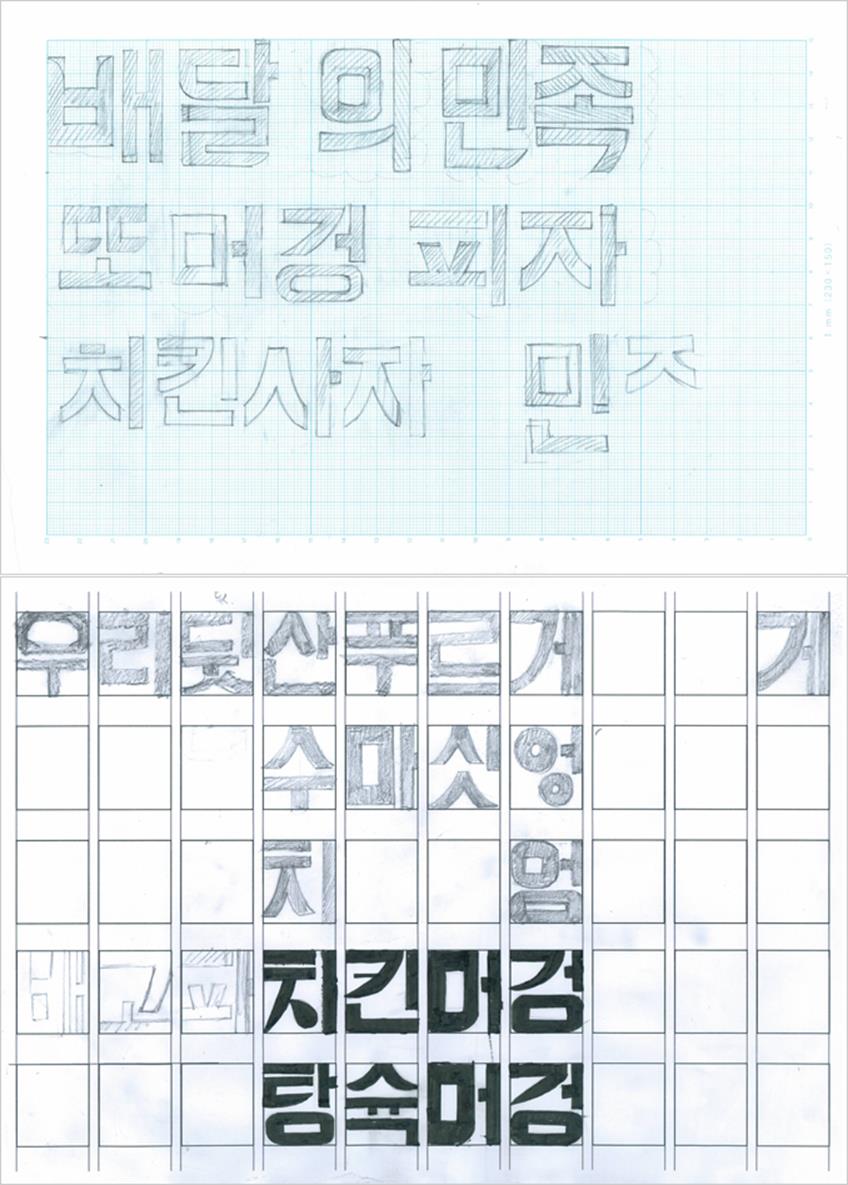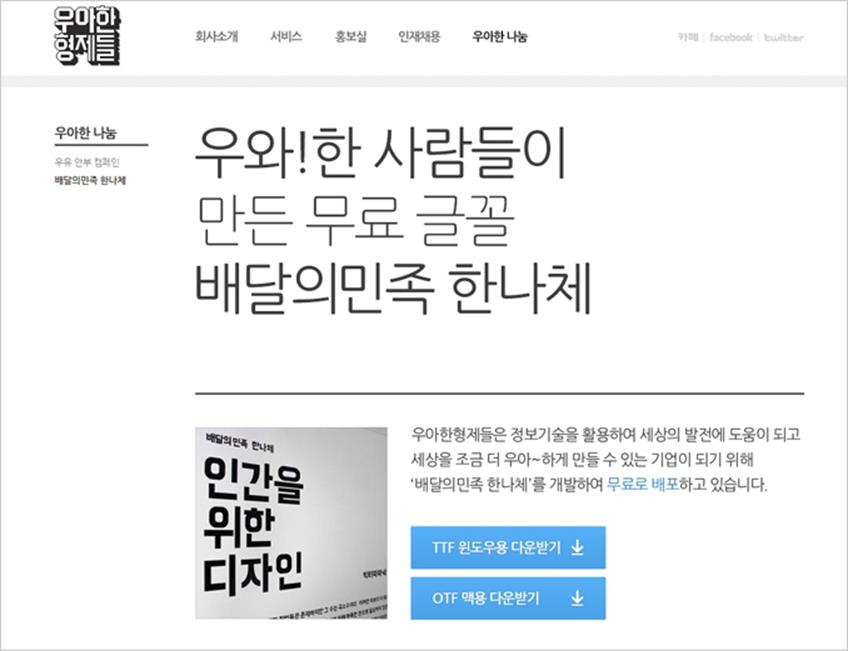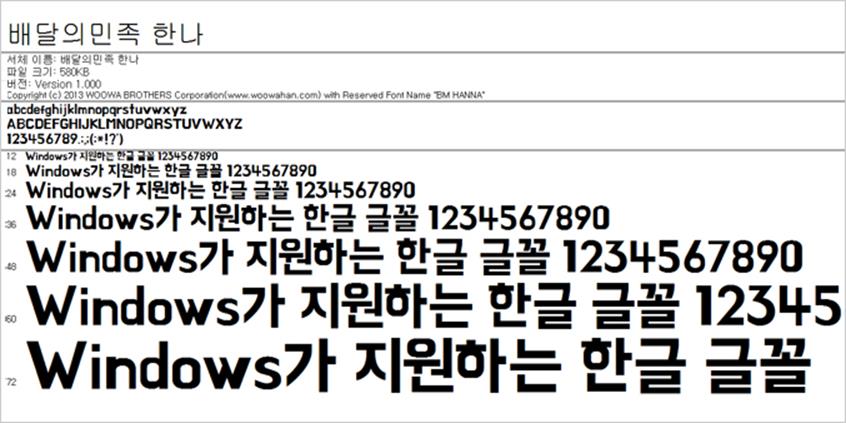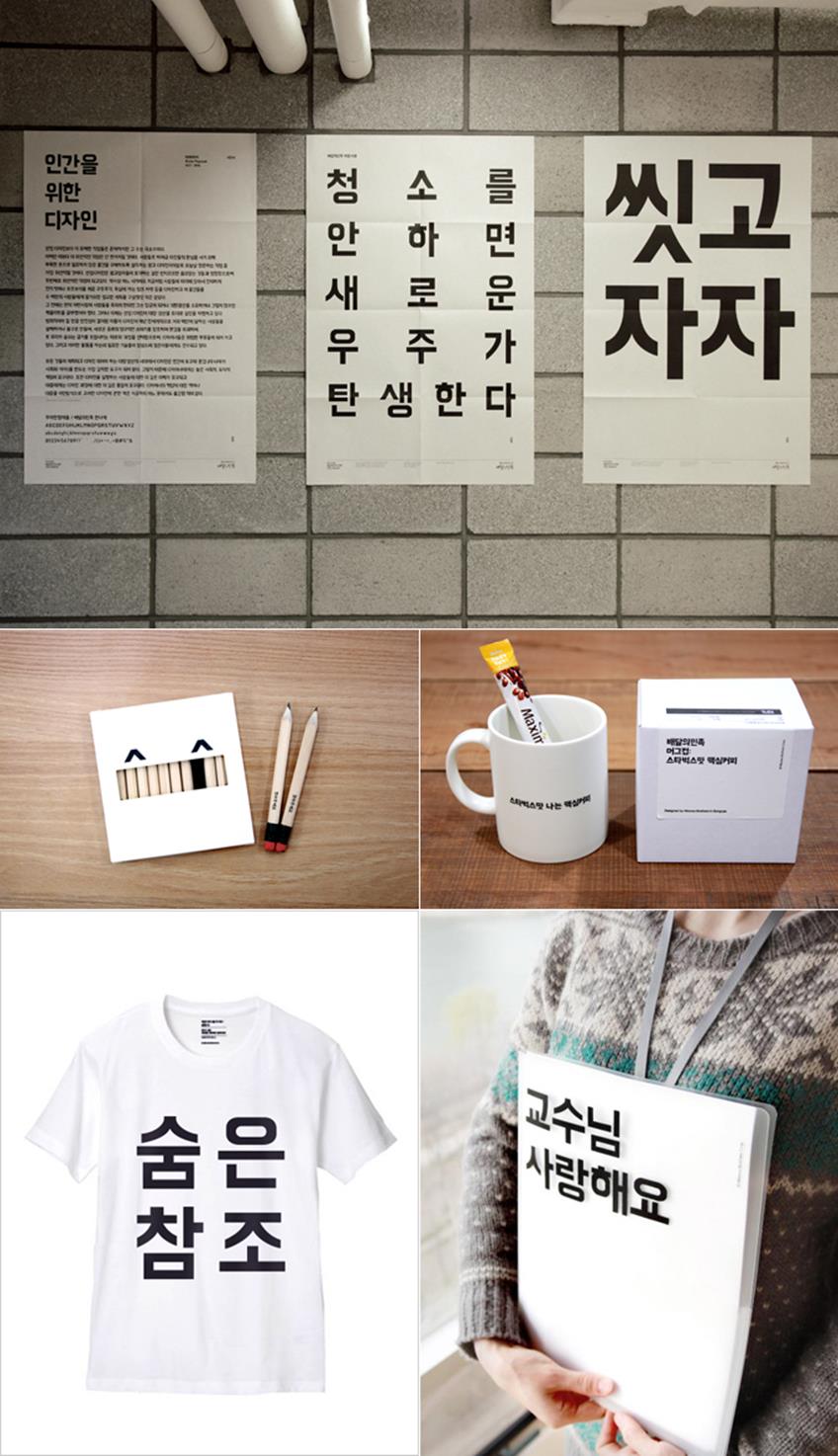
우아하게 경영하는 디자이너, 김봉진
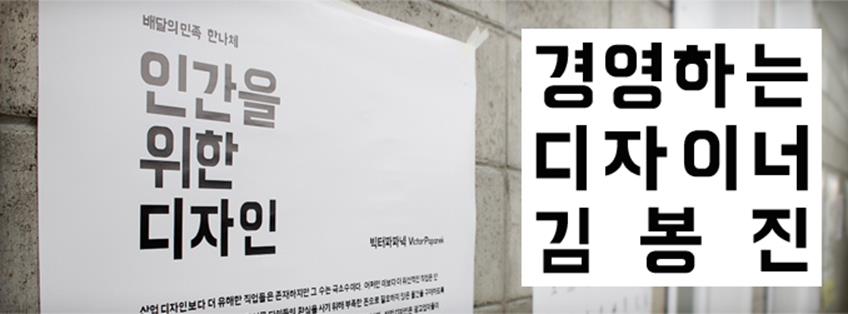
대표님 안녕하세요. 모르는 분이 많지 않겠지만, 간단한 소개를 부탁 드릴게요.
안녕하세요. 저는 우아한형제들(www.woowahan.com)의 김봉진 대표입니다. 우아한형제들은 ‘배달의 민족(www.smartbaedal.com)’이라는 애플리케이션을 개발한 곳이에요. 현재 위치를 중심으로 가장 가까운 배달 업소를 알려주는 서비스죠. 메뉴이미지, 업소 상세정보, 이용후기 등을 제공해 편리하게 배달 음식을 주문할 수 있도록 도와주는 앱이에요. 얼마 전 600만 다운로드를 돌파했고, 5월에는 구글(Google) 초청으로 세계개발자대회(I/O)에도 참석합니다. (웃음) 그리고 저는 2000년도부터 시작해 만 14년 정도 웹 디자이너로 일해온 디자이너이기도 합니다. 네오위즈, 이모션 등에서 경험을 쌓고 한때 인테리어 분야 창업을 했다가 한차례 실패해 보고, NHN과 플러스엑스를 거쳐 지금의 우아한형제들을 창업해 배달의민족 서비스를 만들어 사업을 키워나가고 있죠.
김봉진 우아한형제들 대표
웹 디자이너로 활약하실 때 처음 뵙고, 인테리어 사업을 시작하실 때 마지막으로 인사 드렸는데, 그 이후에 많은 변화가 있었네요.
10년 차 디자이너가 되면 ‘나는 어떤 디자이너로 성장해야 하나?’ 진지하게 고민을 하게 됩니다. 그때 인테리어 관련 사업(봄봄하우스)을 하겠다는 계획을 하고 준비하기 시작했죠. 결국 그 일은 실패했어요. 판매하던 가구와 소품들은 예쁘고 완성도가 높았지만 문제는 제품이 비싸서 팔리지 않았다는 거죠. 그땐 몰랐어요. 많은 디자이너들이 나중에 돈을 모으면 멋진 카페나 펜션을 꾸며 운영하겠다는 계획을 세우지만, 간판이나 메뉴판만 그럴듯하게 만든다고 해서 성공하지 못하는 것과 같죠. 원두 고르는 법이나 에스프레소 추출법도 모르는데 카페가 잘 될 리 없잖아요.
저도 가구의 원가, 물류비 등을 전혀 공부하지 않고 시작했기 때문에 팔수록 손해 보는 상황이었어요. 실패하고 많이 낙담하긴 했지만 의미 있는 경험이었습니다. 그리고 나서 NHN에 2년 정도 있었어요. 그때 많이 배우고 자극도 받았죠. NHN의 젊은 디자이너들과 UXDP 행사에 참여한 머리 좋고 감각적인 대학생들을 보면서 다시 디자인을 배워야겠다는 생각이 들었죠. 포토샵만 잘 해서는 더 이상 성장하긴 어렵겠구나 싶었어요. 본질에 대한 공부와 고민이 필요한 시점이었죠. 디자인 기능공처럼 클라이언트 요구에 맞춰 기계처럼 시안을 만들어내고 PSD 파일을 예쁘게 꾸미는 작업만 해서는 안되겠다 싶었습니다. 그때부터 텍스트가 있는 책을 보고 대학원에 들어가 공부를 시작했죠.
김봉진 대표가 진행했던 프로젝트.
위에서부터 현대카드(2004년), 나이키(2003년), 네이버(2009년)
새로운 도약의 발판이 되어준 ‘배달의민족’은 어떻게 만들어졌는지 궁금합니다.
저는 신명섭, 변사범 디자이너와 함께 플러스엑스(www.plus-ex.com)를 시작했던 창업멤버에요. ‘배달의민족’ 서비스는 플러스엑스의 토이프로젝트였죠. 전략적으로 비즈니스 해야겠다는 생각 없이 주변 사람들이 쓰면 좋겠다는 생각으로 만들었는데 기대 이상의 인기를 끌게 되었어요. 첫 사업을 실패할 때도 느꼈지만 ‘세상은 내가 계획한대로 돌아가지 않는구나’ 싶었죠. 예상하지 못했던 곳에서 제 갈 길을 찾게 된 것 같아 신기했어요.
우아한형제들을 기점으로 ‘디자이너’에서 ‘경영인’으로 모드가 전환된 건 아닌가요?
제 중심은 항상 디자이너에요. 저는 스스로 ‘경영하는 디자이너’라고 정의합니다. ‘디자이너 출신’이란 표현은 과거형이잖아요. 계속 디자인을 하고 있기 때문에 ‘경영’을 앞에 붙였어요. 수많은 CEO들이 경영학적으로 디자인을 논하며 ‘디자인경영’을 말하지만 미술 전공자가 경영을 이야기해도 재미있을 것 같아요. 이미 실리콘벨리에서는 경영하는 디자이너를 어렵지 않게 볼 수 있어요. 회사 가치가 2조를 넘는 에어비엔비(www.airbnb.co.kr) 대표도 디자이너이고 그루폰(www.groupon.com)을 만든 사람도 웹디자이너 출신이에요. 유투브의 공동창업자도 디자이너죠. 그쪽에선 디자이너스펀드가 만들어져 활성화되어 있을 정도에요.
이젠 감성이 중요한 시대입니다. 개발자와는 다른 관점에서 디자이너의 강점이 발현되는 부분이 많다고 생각해요. 새로운 가능성을 보여줄 수 있다고 믿습니다. 브랜드를 만들어가는 일관성, 인사정책, 커뮤니케이션 방법, 의사 결정 방법도 달라요. 예를 들어, 우아한형제들에서는 직원들의 의견을 모아 버킷리스트(bucket list)를 만들어요. 직원들이 원하는 회사 모습을 함께 그리고 공유하는 시스템이죠. 단순히 “우리 이렇게 해요”라는 구호를 적고 파워포인트로 보여주거나 사장님 훈시처럼 액자에 담아 걸어두는 방식이 아니라 포스터를 만들어 사무실 곳곳에 부착해 직원들과 커뮤니케이션 하고 비전을 명확하게 전달하는 방식이죠.
저는 계속 디자인을 하고 있어요. 디자이너가 아니면 생각하기 어려운 다양한 시도를 하고 있습니다. ‘한나체’라는 폰트를 만든 것도 그렇고 어렵게 만든 폰트를 무료로 배포하겠다는 생각도 회사 대표가 디자이너가 아니었다면 쉽게 이루어지지 않았을 거에요. 대기업이 아닌 이렇게 작은 조직에서 그런 일을 계획하고 결정하기는 쉽지 않죠.
배달의민족의 전반적인 디자인 컨셉이나 전략에 대해 소개해주세요.
저는 일을 시작하기 전에 먼저 정의를 내려봐요. 책을 보면서 전략과 컨셉을 만들어가는 방식을 공부하고 제게 맞는 방식을 찾은 거죠. 예전엔 그러지 않았어요. (웃음) 예를 들어 ‘커피’에 대한 사전적 의미를 찾고 나만의 커피를 정의 내리는 거죠. 배달 음식점을 알려주는 서비스를 만들어보자고 했을 때에도 ‘배달 음식’에 대한 정의를 내리고 디자인과 브랜드를 고민하기 시작했어요.
저는 ‘배달 음식’ 하면 국가대표 축구 경기를 할 때 친구들과 치킨에 맥주를 배달해 먹었던 시간, 밤 11시가 넘는 시간까지 직원들과 일하다 족발에 보쌈을 배달해 먹으며 토론을 이어가던 시간들이 생각났어요. 그래서 “아, 배달 음식이란 사랑하는 사람들과 나누는 행복한 시간이구나!”했던 거죠. 그렇기 때문에 배달 음식을 검색하고 찾는 과정도 즐겁고 재미있으면 좋겠다고 생각했어요. 애플리케이션을 구동하는 순간부터 재미있게 만들자. 그래서 이름도 ‘배달의민족’이라고 정하고 ’21세기최첨단 찌라시’, ‘전단지백과사전’과 같은 카피들도 직접 생각해냈죠.
우아한형제들 CI, 배달의 민족 BI, 이벤트 페이지, 캐릭터 모음
전반적인 디자인은 홍대 문화를 좋아할법한 대학생을 대상으로 삼고 키치, 패러디 등과 같은 키워드에 접목했어요. 이미 <무한도전>, <컬투쇼>와 같은 비주류 느낌의 문화 코드가 자리를 잡고 인기를 끌고 있잖아요. ‘쌈지’의 디자인 느낌을 좋아해서 참고하고 메인 폰트는 윤디자인의 사춘기체로 정했죠. 사춘기체를 메인 폰트로 사용한 건 무리라는 의견이 많았지만 과감하게 사용했어요. 그렇게 아이덴티티가 다져졌죠. 배달의민족이 인기를 끌면서 우후죽순 사춘기체를 너무 많이 사용해 우리만의 폰트를 만들어보자는 생각을 갖게 되기도 했죠.
일반적인 브랜드들이 정중한 학생회장 느낌에 머리도 좋고 운동도 잘하는 ‘엄친아’ 스타일을 추구했다면, 우리는 박명수처럼 친근한 동네 형 느낌을 추구했습니다. 애플이나 네이버, 현대카드 등의 브랜드가 차지하고 있는 영역은 모두 비슷해요. 스마트하고 세련되고 고급스럽죠. 반면에 우리는 그 반대편에 있는 B급, 키치, 저속, 패러디 등의 키워드가 어울리는 영역을 선택했죠. 브랜드는 세련되어야 한다고 생각하지만 우리는 타깃도 다르고 관점이 다르기 때문에 의도된 저급 컨셉으로 전략을 짜고 움직인 셈이죠.
최근 송파로 사무실을 이전하시면서 인테리어에도 굉장히 신경을 많이 쓰신 것 같은데요. 공간에 대한 소개도 부탁 드릴게요.
제가 직접 설계하고 디자이너와 세부적인 아이디어를 나눠 공간을 꾸몄어요. 우아한형제들의 사람들이 머무는 공간은 어떠해야 하는지 우리 스스로 하나씩 풀어갔죠. 특징 중 하나는 대회의실 문을 모두 개방할 수 있는 폴딩 도어로 만들었다는 점이에요. 문을 모두 열면 80여 명이 강의를 들을 수 있는 공간이 확보되죠. 대회의실은 가장 낭비가 심한 공간이에요. 회의가 이루어지지 않을 땐 거의 죽어있는 공간이죠. 그래서 사용하지 않을 땐 카페처럼 열어둘 수 있게 했습니다. 우리처럼 작은 회사에서는 공간을 최대한 효율적으로 쓰는 방법을 고민하게 됩니다. (웃음) 위치 선정은 앞서 얘기한 버킷리스트에 의해 정해졌어요. 번잡한 강남 한복판 말고 공원이 옆에 있는 한적한 곳에서 일하고 싶다는 직원들이 많았어요. 공간을 찾던 중에 마침 석촌호수를 앞에 두고 매직아일랜드와 송파나루공원이 있는 이곳을 운 좋게 찾게 되었죠. 전철역에서 15분 정도 걸어와야 하는 위치에 있지만 공원을 끼고 걸어오는 길이 좋아요. 공간 내부는 피터팬에 나오는 네버랜드가 컨셉이에요.
우아한형제들 사옥에 대한 계획도 있나요?
사옥을 직접 설계하고 짓는 일은 많은 디자이너들이 꿈꾸는 일 아닐까요? (웃음) 몇 년 후에 실현 가능할지 모르겠지만 꼭 해보고 싶은 작업이에요. 우아한형제들 사옥 1층과 2층에는 어린이 집을 만들고 싶어요. 사원 복지를 위한 일이기도 하지만 디자이너가 만드는 어린이 집은 어떤 모습이 될지 궁금해요. 생각만해도 설렙니다. 어린이를 위한 교육 공간, 아기와 엄마 그리고 선생님 사이의 정서적 교감, 많은 사람들의 경험을 모두 고려해 디자인해야 특별한 공간인만큼 굉장히 재미있을 것 같아요. 물론, 사옥에 대한 이야기는 어디까지나 꿈입니다. (웃음)
회사 운영이나 직원과의 관계에서 가장 중시하고 신경을 쓰는 부분은 무엇인가요?
‘성장’입니다. 10년 넘게 직장 생활을 해봤고 이제 14년 차에 접어드는데요. 가장 아름답고 행복하게 기억하는 순간은 많은 월급과 좋은 복지 때문이 아니었어요. 죽도록 일했지만 이모션(www.emotion.co.kr)에서의 시간들이 소중한 이유는 함께 꿈을 나누며 성장했던 친구들이 있었기 때문이에요. 이모션은 제게 친정 같은 회사죠. 그때 지금 이루고 있는 네트워크 기반을 형성했고, 그 시절 열심히 일한 덕분에 많은 분들이 ‘김봉진’ 하면 성실한 친구로 기억해주고 있어요. 힘들었지만 돌이켜보면 그때가 가장 행복했고, 제가 가장 많이 성장했던 시절입니다.
우아한형제들의 명함이, 우리 공간이, 우리 디자인이 누군가에게 이야기 거리가 되면 좋겠어요. 단순히 “예쁘다”로 끝나지 않고 다른 사람을 만났을 때 우아한형제들의 명함과 공간이 어떻더라고 재미있게 전하고 싶은 재미와 즐거움을 줄 수 있으면 좋겠어요. 그런 재미있는 장치들이 모여 자연스럽게 우아한형제들의 문화가 된다고 생각합니다. 브랜드 위에 문화가 있어요. 백제와 고구려가 망해도 그들의 문화가 지금까지 남아있듯이 문화가 만들어지면 쉽게 무너지지 않는 자존심이 생깁니다. 그게 우아한형제들의 힘이 되겠죠.
그리고 해외의 경영하는 디자이너들을 보면서 우리도 새로운 길을 걸을 수 있겠다는 생각을 합니다. 가능성을 봤어요. 오랜 시간 클라이언트 일을 받아서 2~3개월씩 용병처럼 투입되어 디자인 작업을 해왔지만 이제 호흡이 긴 디자인을 해보고 싶어요. 어떤 결과물이 나올지 모르지만 만들어보고 싶어요. 일반인들이 생활 속에서 흔하게 접하는 서비스를 잘 만들어서 사람들이 말하는 잣대의 성공 케이스를 만들어 보여드리고 싶습니다. 그렇게 하면 다른 디자이너들에게 새로운 길을 열어줄 수 있지 않을까 하는 기대도 있습니다. 지켜봐 주세요.